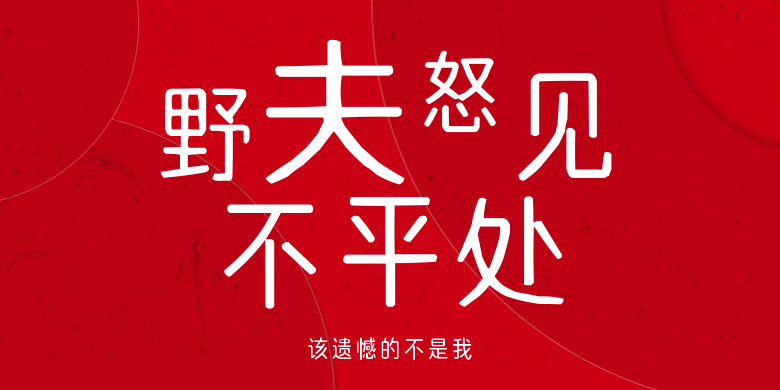
该遗憾的不是我
该遗憾的不是我,这款字体结构工整、笔画清晰,兼顾美观与易读性,适用于标题、正文、海报、包装、LOGO 等多种场景。字形优雅稳定,风格百搭耐看,适配日常排版与创意设计,让文字呈现更舒适、更具质感。该遗憾的不是我一笔一画,皆是细节,以均衡的比例、流畅的线条打造舒适视觉体验,字形端正大气,风格简约现代。无论是商业设计、品牌宣传还是日常排版,都能轻松驾驭,让文字更有格调与力量。该遗憾的不是我字体下载。